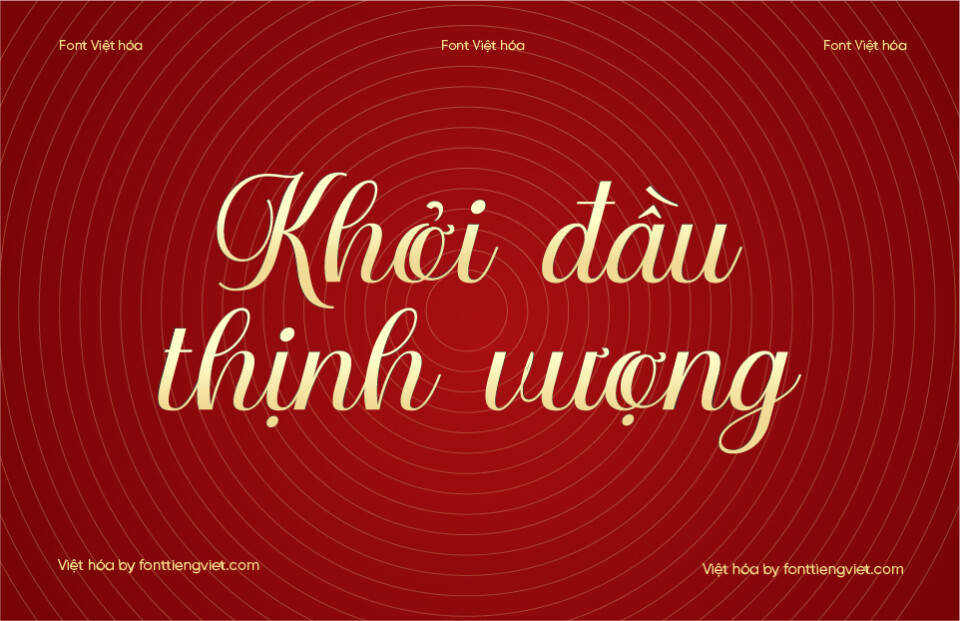
Font Việt hóa 1FTV VIP Jasline – Đẳng cấp tinh tế cho mọi thiết kế đồ họa
Giới thiệu về Font Việt hóa 1FTV VIP Jasline
Trong thế giới sáng tạo, việc lựa chọn một bộ Font Chữ phù hợp đóng vai trò quyết định đến thẩm mỹ của tác phẩm. Font Việt hóa 1FTV VIP Jasline là một trong những bộ font chữ hiện đại, mang đậm phong cách thanh lịch và sang trọng. Được tinh chỉnh kỹ lưỡng về dấu tiếng Việt, bộ font này giúp người dùng dễ dàng ứng dụng vào các dự án thiết kế mà không lo lỗi hiển thị. Với các đường nét mềm mại nhưng vẫn giữ được sự ngay ngắn, Jasline hứa hẹn sẽ mang đến một làn gió mới cho cộng đồng Designer tại Việt Nam.
Ưu điểm nổi bật của bộ Font Việt hóa 1FTV VIP Jasline
Nét chữ thanh thoát và tính ứng dụng cao
Đặc điểm nổi bật nhất của Font Việt hóa 1FTV VIP Jasline chính là sự kết hợp hoàn hảo giữa tính cổ điển và hơi thở đương đại. Các ký tự được thiết kế với độ tương phản nhẹ, tạo cảm giác dễ chịu cho mắt người đọc. Điều này cực kỳ quan trọng trong môi trường giáo dục, giúp học sinh và giáo viên trình bày bài giảng một cách trực quan và chuyên nghiệp hơn.
Tương thích đa nền tảng cho người dùng
Kết luận và trải nghiệm bộ font chuyên nghiệp